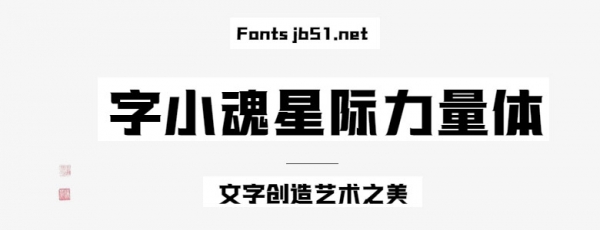
字小魂星際力量體是由字魂字庫(kù)推出的藝術(shù)字體,這款字體筆觸適中,字形大氣且端正,具有很好的視覺(jué)感,適合應(yīng)用于藝術(shù)設(shè)計(jì)、平面宣傳設(shè)計(jì)、網(wǎng)頁(yè)設(shè)計(jì),書(shū)法字帖等領(lǐng)域。
字小魂星際力量體字體是一款可商用的黑體字體,該字體包含6763個(gè)中文、字母、 符號(hào)和數(shù)字,具有簡(jiǎn)約的風(fēng)格,可以滿(mǎn)足您設(shè)計(jì)上的各種需求,該字體主要用于黨政公務(wù)等場(chǎng)景, 您不但可以在字魂網(wǎng)下載字小魂星際力量體字體,同時(shí)還有眾多毛筆書(shū)法字體、創(chuàng)意字體等可供選擇!